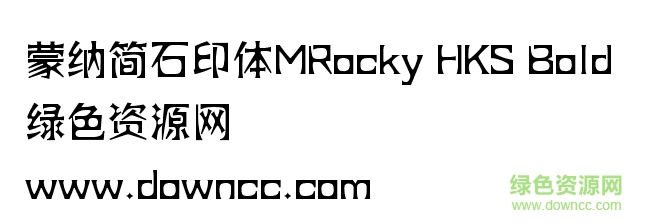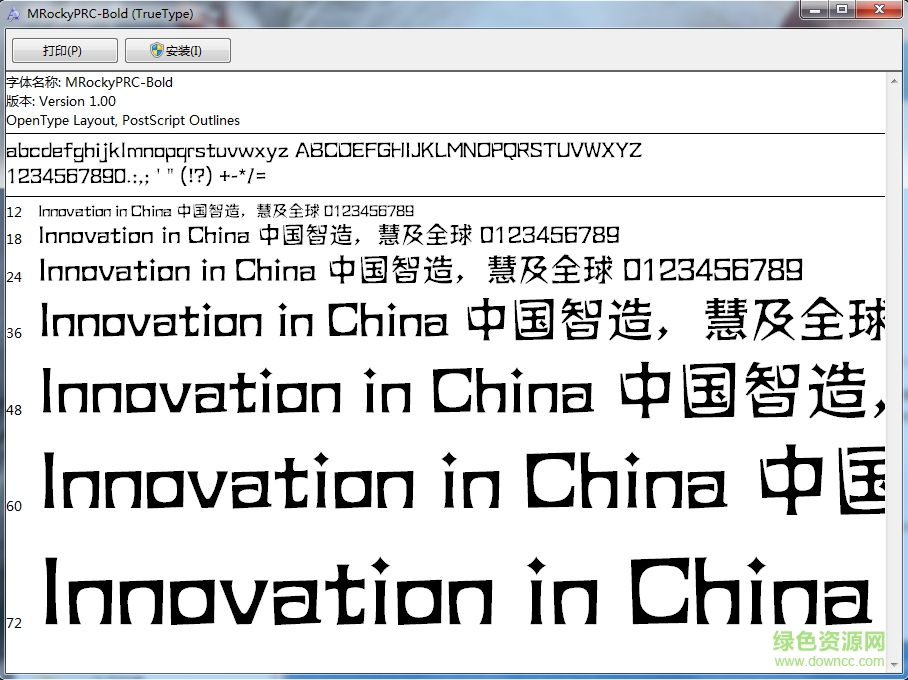
蒙納石印簡
蒙納簡石印體是一款造型和字跡都很優(yōu)美的蒙納字體,可將部分繁體字體轉(zhuǎn)換成簡體中文,歡迎大家在綠色資源網(wǎng)免費下載!
蒙納石印簡體介紹
蒙納簡石印體 MRocky HKS Bold,是面向港澳臺地區(qū)使用的字體,所以在使用時您輸入的部分簡體字可能顯示不出來,這時您需要將您輸入的簡體字轉(zhuǎn)換成繁體字才能正常顯示!
蒙納簡石印字體